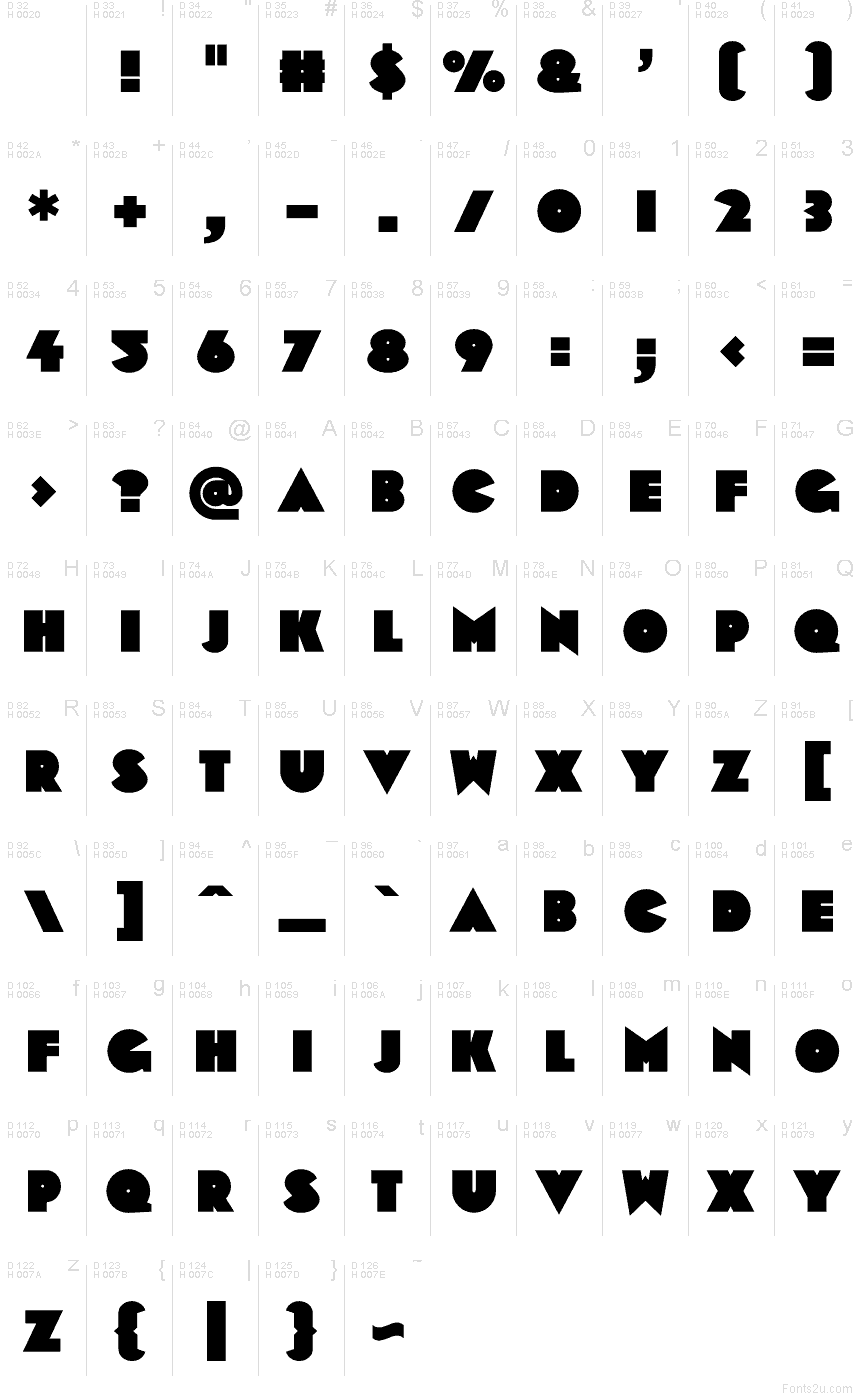
Hyperbonnard
Hyperbonnard je bezplatné retro display písmo s masívnymi geometrickými literami a hravým nádychom 70. rokov. Široké krivky sa v ňom spájajú s ostrými trojuholníkmi, hlbokými zárezmi a tesne priliehajúcimi tvarmi. Kruhové výrezy dotvárajú husté siluety písmen.
Dokáže premeniť nadpis na pôsobivý emblém pre hudobné plagáty, obaly platní či festivalovú grafiku. Neobvyklé spoje sa výborne hodia aj pre módne značky a reklamné predmety postavené na výraznom, kompaktnom nápise. Svoju najsilnejšiu stránku ukazuje v nadrozmerných titulkoch, kde meniace sa tvary pôsobia ako logo na mieru.